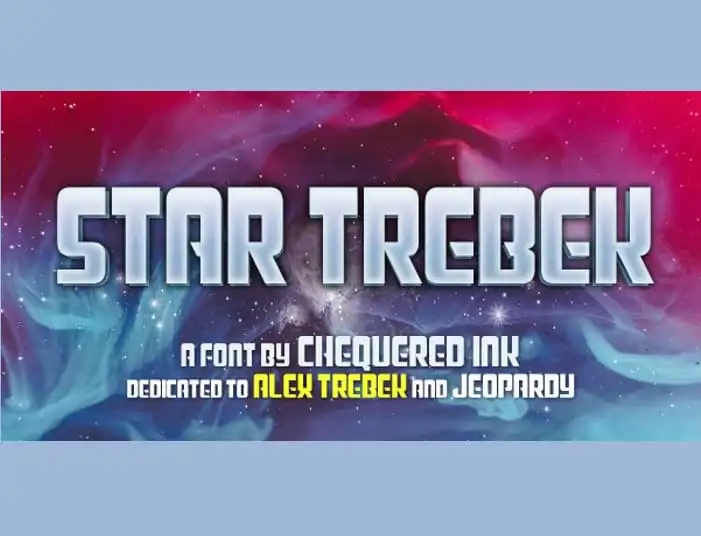
Star Trebek Display Font – Fonte Grátis
Star Trebek Display Font
Descubra a fonte Star Trebek Display Font, uma elegante tipografia de destaque projetada para enriquecer qualquer projeto visual. Inspirada na cultura urbana contemporânea e pela espiritualidade medieval, essa fonte multipropósito oferece um toque único que combina elementos estilizados dos tempos medievais com a frescor da moda streetwear atual. Perfeita tanto para aplicar em rótulos de produtos, como na criação de logos ou banners, Star Trebek Display Font é uma opção versátil e moderna. Suas linhas arredondadas e formas geométricas criam um visual atraente que transmite confiança e estilo. Não hesite em explorar mais sobre essa fonte para tornar seus projetos de design ainda mais memoráveis. Embora Star Trebek Display Font não possua referências explícitas ao personagem do famoso apresentador de quiz, há uma conexão estética entre seu design elegante e a cultura da televisão. Esta é uma fonte que combina as características modernas com elementos históricos, tornando-a perfeita para aqueles que buscam algo distinto em suas criações visuais.